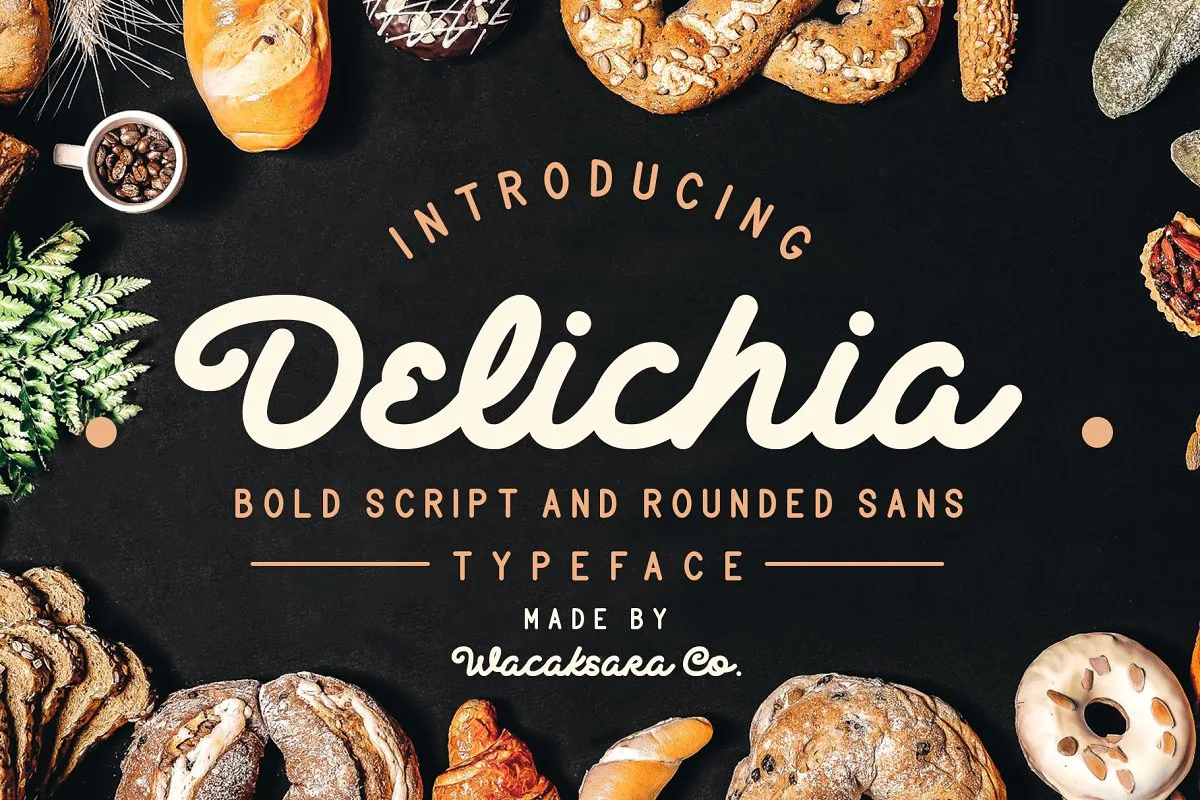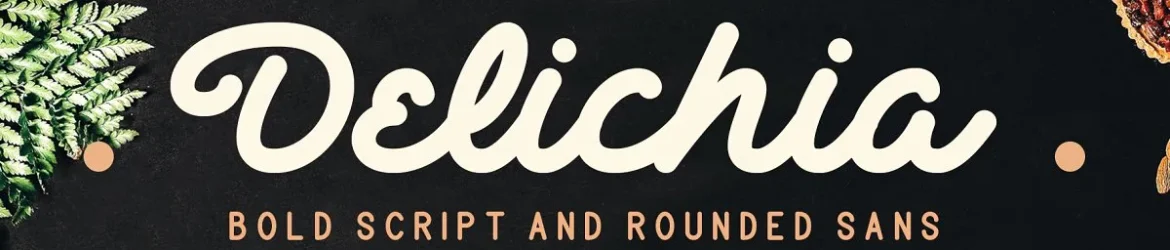
A fonte Delichia Bold Script é uma opção envolvente para designers e criativos que buscam uma mistura única de estilo script e sans-serif. Com a sua escrita elegante embutida em gestos dramáticos limpos, essa fonte se destaca por sua beleza surpreendente e facilidade de uso. A Delichia foi projetada pela Wacaksara Co. e apresenta um duplo estilo: um script bold ligado em movimentos assertivos e uma tipografia sans-serif redonda. Inspirada pelo aroma dos pães frescos, a Delichia é perfeita para criar design que chama atenção. Ideal para logotipos de empresas, menus de restaurantes, rótulos de produtos, materiais impressos, identidades visuais, postagens nas redes sociais e textos sobrepostos a qualquer imagem. Não importa o contexto, Delichia tem um toque único que certamente dará sua arte um gosto refinado.